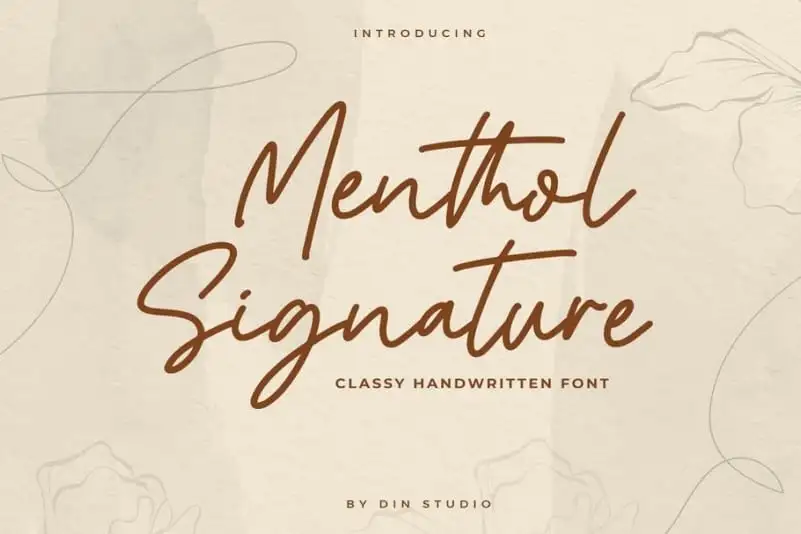
Menthol Signature – Handwritten Font – Download Grátis
A Menthol Signature é uma nova adição à coleção de fóruns modernas e elegantes criadas pelo designer Hamilton. Esta fonte é a perfeita escolha para qualquer projeto profissional, seja para criar um logotipo ou apenas personalizar o nome de sua marca. Menthol Signature é um tipo de linha única que oferece uma aparição minimalista e contemporânea, com linhas finas e sutis que criam um ar cuidadosamente pensado. Cada letra apresenta nuances únicas e belas características, tornando a Menthol Signature perfeita para quem busca personalidade em seus materiais de marca. A grande vantagem desta fonte é o seu extenso conjunto de alternativas e swashes. Com esses recursos, você pode dar um toque único ao logo ou à sua marca que vai além da tipografia padrão. Uma vez mais, Menthol Signature oferece aos designers a possibilidade de criar uma aparência personalizada, inspirada na arte da calligrafia. Com certeza é o tipo perfeito para quem busca uma mistura de elegância moderna e personalização cuidadosamente elaborada no seu projeto visual. Atrativo, funcional e estiloso, Menthol Signature é uma excelente escolha para quem procura uma fonte perfeita para qualquer projeto de marca ou arte digitais.